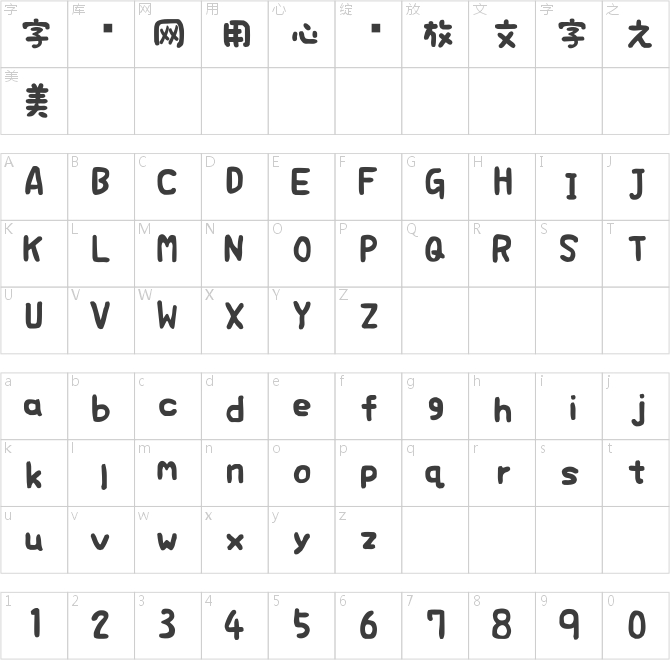
えるまーフォント<等幅> ver.1.60
えるまーPフォント<プロポーショナル> ver1.60
マジックペンで書(shū)いたような手書(shū)きフォントです。<第二水準(zhǔn)まで>
足跡やハート等が罫線の後半に入っています。「けいせん」を変換させてみてください。
豆豆字體えるまー字體ElmeFont字庫(kù)是一款讓人賞心悅目、百看不厭的日文字體,適合各類(lèi)廣告和產(chǎn)品包裝設(shè)計(jì)應(yīng)用,字體大小3.26MB,格式為ttf字體,上傳用戶是lvpyt,作者/版權(quán)方為隠れ家